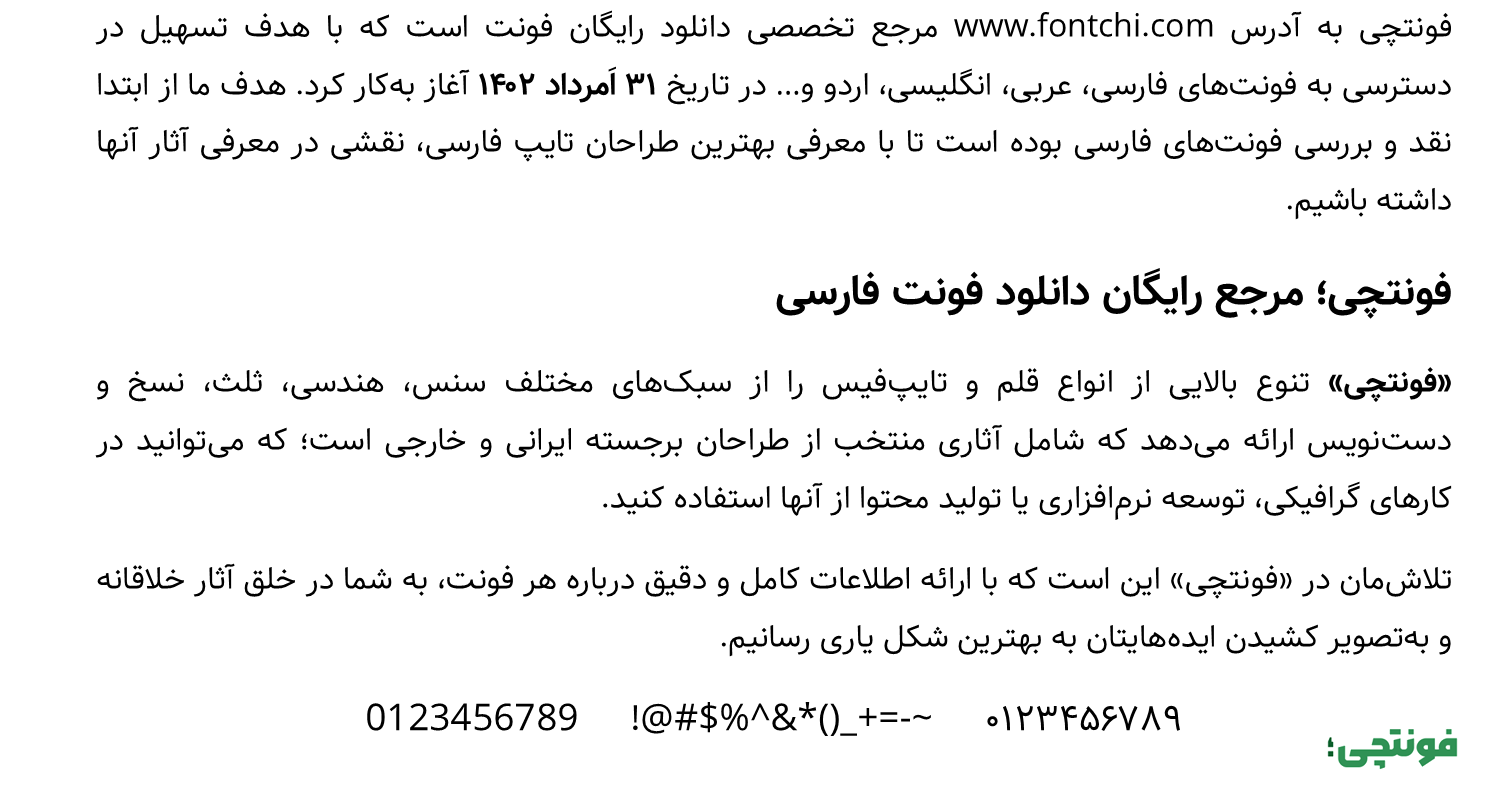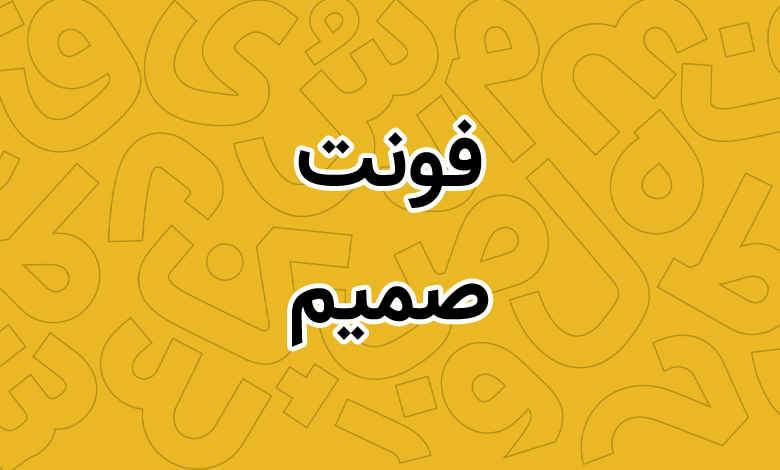
فونت صمیم (Samim)
فونت صمیم (به انگلیسی: Samim) یکی از قلم‌های محبوب فارسی برای طراحی گرافیک و استفاده به‌عنوان وب‌فونت است که توسط زنده‌یاد صابر راستی‌کردار در سال ۱۳۹۴ طراحی و توسعه یافته است. این فونت با هدف ایجاد یک تایپ‌فیس خوانا و زیبا برای استفاده در محیط‌های دیجیتال و چاپی طراحی شده و به‌سرعت جایگاه ویژه‌ای در بین طراحان و توسعه‌دهندگان وب پیدا کرده است.
فونت صمیم در دسته‌ی فونت‌های سنس‌سریف (Sans-Serif) قرار می‌گیرد که به دلیل نداشتن زواید در حروف، خوانایی بالایی در صفحه‌نمایش‌های دیجیتال دارد. این فونت بر مبنای قلم وزیر ساخته شده که خود بازطراحی فونت DejaVu ۲.۳۵ می‌باشد.
در ادامه به بررسی کامل فونت صمیم رایگان پرداخته و با تکیه بر ویژگی‌ها و کاربردهایی که این فونت دارد آن را از نظر اینکه برای استفاده در چه محیط‌هایی مناسب است مورد ارزیابی قرار می‌دهیم.
معرفی و دانلود فونت صمیم (Samim)
فونت صمیم به دلیل طراحی ساده و خوانا، دارای کاربردهای متعددی است؛ ازجمله:
• فونت وب‌سایت: خوانایی بالا و ساختار مناسب حروف از نظر طراحی، این فونت را به گزینه‌ای ایده‌آل برای استفاده در فضای دیجیتال، خصوصا متون سایت‌ها تبدیل کرده است.
• رابط کاربری (UI): در طراحی اپلیکیشن‌ها و نرم‌افزارها، استفاده از فونت صمیم به بهبود تجربه‌ی کاربری کمک می‌کند. خصوصا اپلیکیشن‌هایی که ایجاد فضای دوستانه و صمیمی در اولیت آنها باشد. مانند اپلیکیشن‌های کتاب‌خوانی در حوزه کودک و نوجوان.
• طراحی گرافیک: در طراحی پوسترها، بروشورها و سایر محصولات چاپی، فونت صمیم به دلیل زیبایی و سادگی، جلوه‌ی خاصی به طرح‌ها می‌بخشد.
• مستندات و مقالات: برای نگارش مقالات، کتاب‌ها و مستندات فارسی، این فونت گزینه‌ای مناسب برای افزایش خوانایی متن است.
صابر راستی‌کردار یکی از طراحان برجسته‌ی فونت در ایران بود که فونت‌های متعددی از جمله وزیر، ساحل، شبنم و صمیم را طراحی کرده است. آثار او به دلیل کیفیت بالا و رعایت استانداردهای طراحی، مورد استقبال گسترده‌ی جامعه‌ی طراحان و توسعه‌دهندگان قرار گرفته است.
پیش نمایش و وزن های فونت صمیم
فونت رایگان صمیم در سه وزن مختلف (معمولی، متوسط و ضخیم) طراحی شده است که امکان استفاده در پروژه‌های متنوع گرافیکی یا استفاده برای فونت سایت را فراهم می‌کند. همچنین، این فونت از اعداد فارسی پشتیبانی می‌کند و نسخه‌هایی با حروف لاتین Open Sans نیز در بسته‌ی آن موجود است که هماهنگی مناسبی بین متون فارسی و انگلیسی ایجاد می‌کند.
فونت صمیم با ویژگی‌های مثبت خود، انتخاب مناسبی برای بسیاری از پروژه‌ها است. خوانایی بالا، طراحی مدرن و پشتیبانی از اعداد فارسی از جمله نقاط قوت این فونت محسوب می‌شوند. همچنین، وجود نسخه‌هایی با حروف لاتین، امکان استفاده‌ی هم‌زمان از متون فارسی و انگلیسی را بدون نیاز به تغییر فونت فراهم می‌کند.
با این حال، در برخی موارد ممکن است نیاز به وزن‌های بیشتری برای کاربردهای خاص احساس شود که در نسخه‌های فعلی موجود نیست. همچنین، در پروژه‌هایی که نیاز به فونت‌هایی با سبک دست‌نویس باشد، این فونت به‌دلیل صمیمیتی که در طراحی دارد می‌تواند گزینه‌ای بین یک فونت رسمی و دست‌نویس باشد.